Café précoce
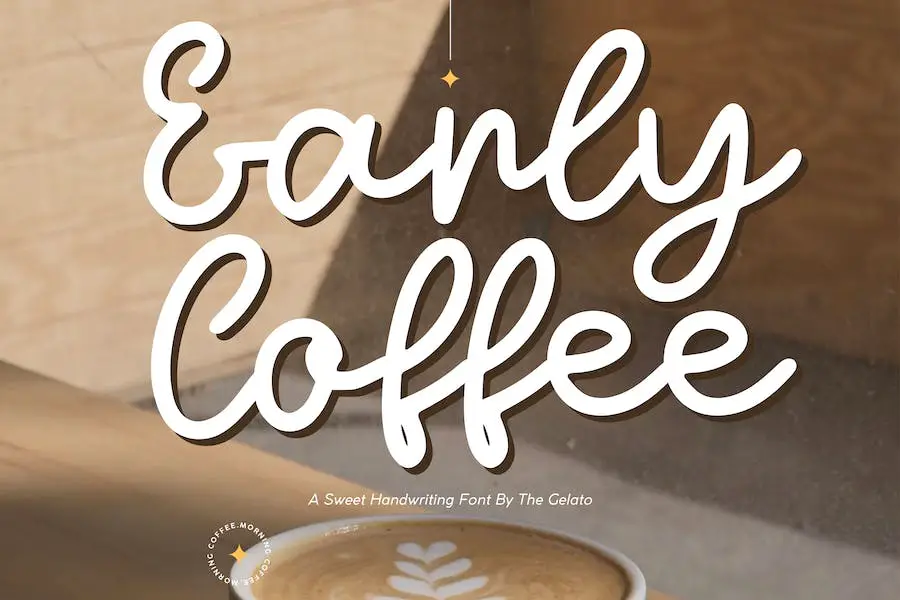
Early Coffee est une police de café moderne qui ajoute une touche d'élégance et de sophistication à tout projet de conception graphique.
Cette police manuscrite est parfaite pour diverses utilisations, notamment comme police de broderie calligraphique, police de café, police de signe de menu de café, police de café manuscrite, police de calligraphie moderne et police cursive monoline.
Avec ses lignes douces et fluides et son aspect cursif, Early Coffee apporte une sensation de chaleur et de charme à vos créations.
Que vous travailliez sur un logo, une signalisation, un menu ou du matériel publicitaire pour une entreprise liée au café, cette police rehaussera votre projet et lui donnera une sensation unique et artisanale.
La polyvalence d’Early Coffee est l’un de ses attributs les plus remarquables. Il s'intègre parfaitement aux styles de design modernes et vintage, ce qui le rend adapté à un large éventail de projets.
Sa structure monoline offre une épaisseur constante sur chaque forme de lettre, garantissant la lisibilité et la clarté quelle que soit la taille.
Café matinal
Coffee Morning est une extraordinaire police sans empattement faite à la main qui en dit long sur ses imperfections. Ses traits rugueux et ses formes imparfaites lui confèrent une saveur unique, tout comme une tasse de café forte et audacieuse le matin.